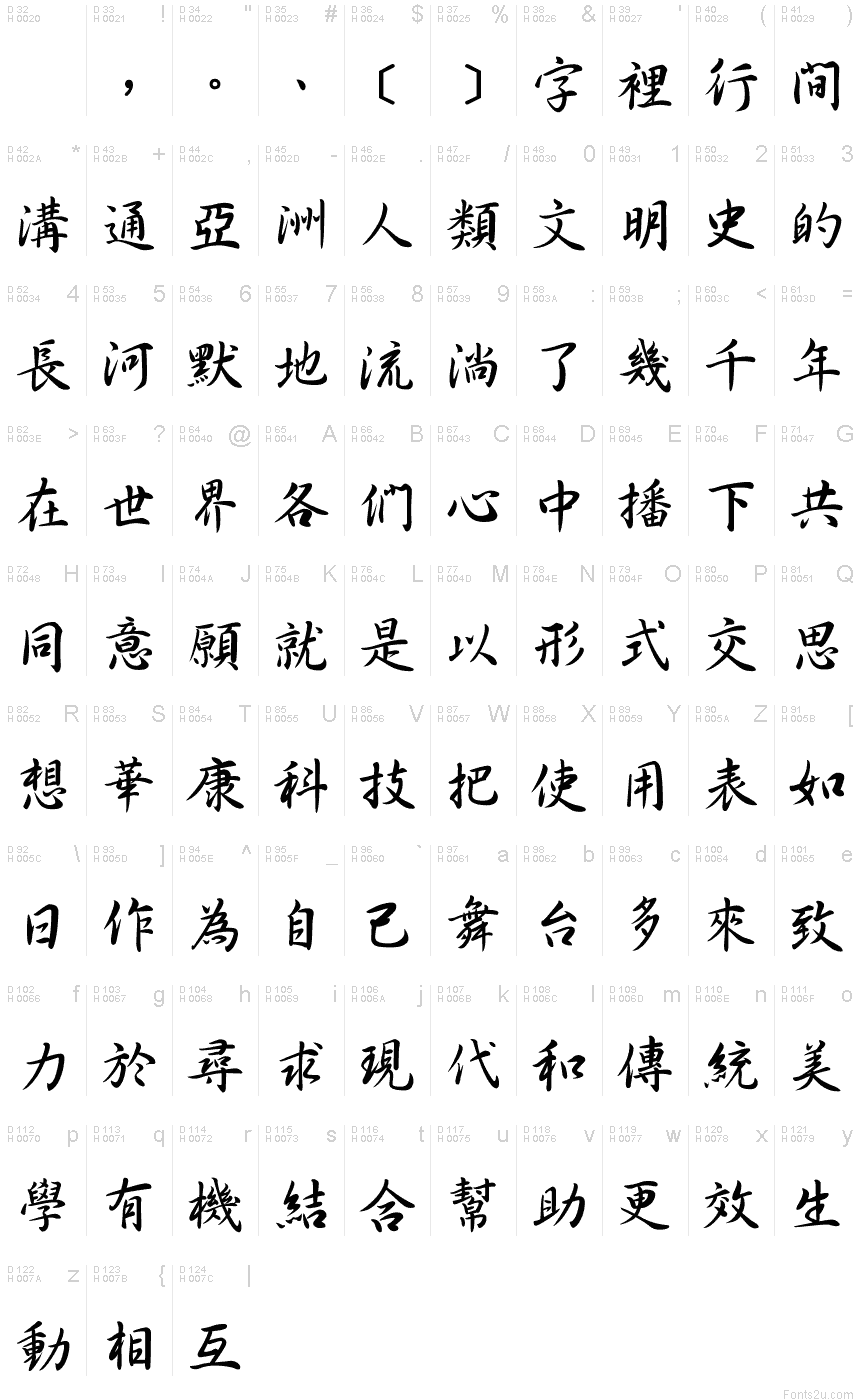
DF Xing Shu Medium 1B von DynaLab Inc. ist eine kostenlose chinesische Pinsel-Schrift im Xing-Shu-Stil, die den lockeren Fluss handgeschriebener Schilder einfängt. Die Buchstaben leben von lebendigen, konisch zulaufenden Strichen und schnellen Richtungswechseln, was dem gesamten Design einen halb-kursiven Rhythmus verleiht, der eher geübt und natürlich als formell wirkt.
Sie eignet sich hervorragend für redaktionelle Headlines, Gastronomie-Branding, Plakate für kulturelle Veranstaltungen, Verpackungsdesign und Titelkarten, bei denen eine menschliche Pinselführung wichtiger ist als strenge Einheitlichkeit. Da es sich um eine kostenlose Schrift handelt, ist sie auch ideal für kurze Cover-Texte, Kapitelanfänge und ausdrucksstarke Logotypes, da die Striche ihre Dynamik und ihren Kontrast selbst bei wenigen, großen Zeichen beibehalten.